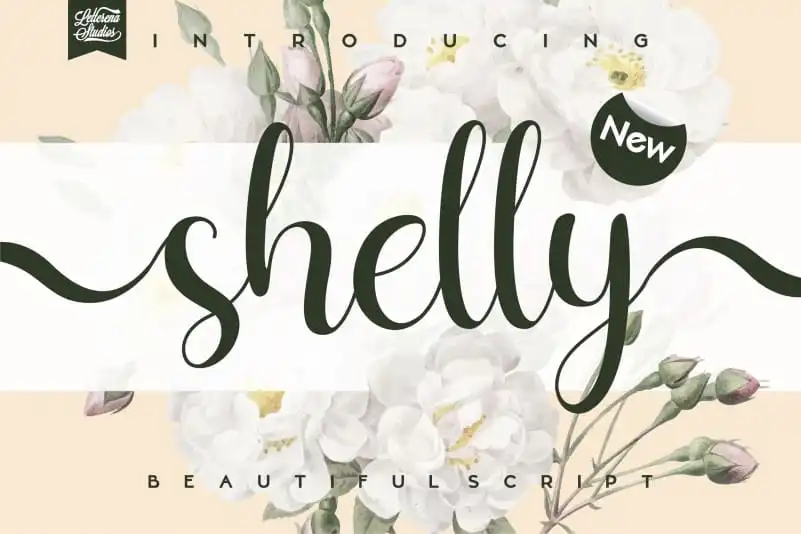
A Shelly Calligraphy Font é uma escolha perfeita para quem procura um estilo elegante e romântico no seu design gráfico. Essa fonte contém linhas suaves e fluidas, inspiradas na calligrafia, mantendo os valores estilísticos de forma clássica enquanto também se sente contemporânea e atual. O fato de ser PUA encoded significa que você terá facilidade para acessar todos os gráficos e swashes desta fonte. Esta elegante escolha permite criar um design com nuances perfeitas, tanto em aparência quanto no uso prático, tornando-a uma opção ideal para designers que valorizam tanto a qualidade quanto a modernidade na sua arte. Seja para aplicativos digitais ou impressos, esta fonte certamente enriquecerá seus projetos gráficos de forma única e sofisticada.